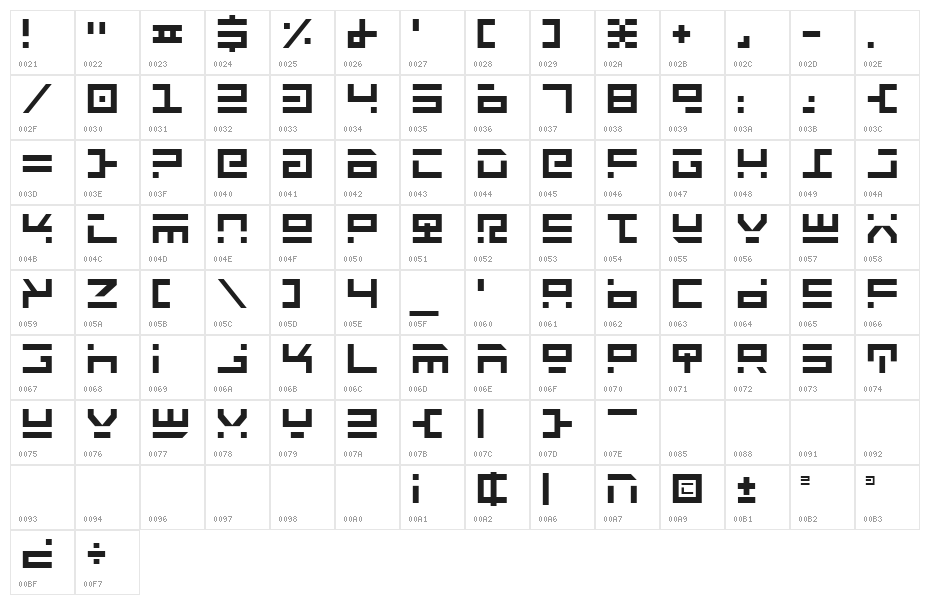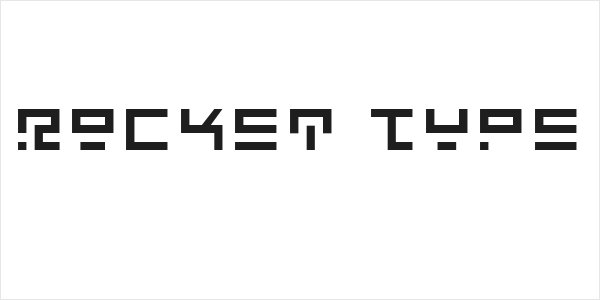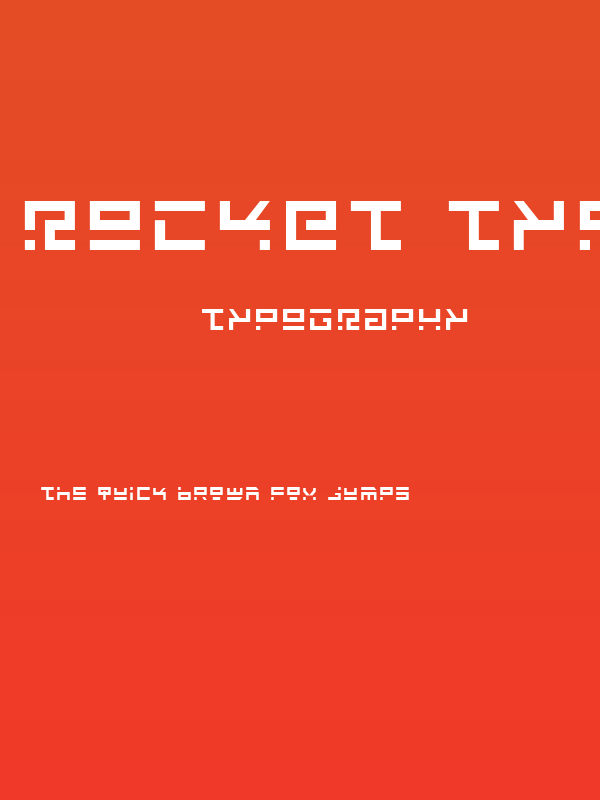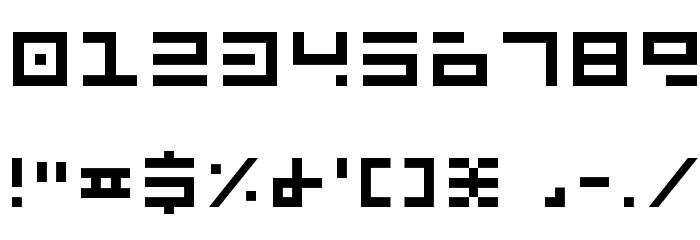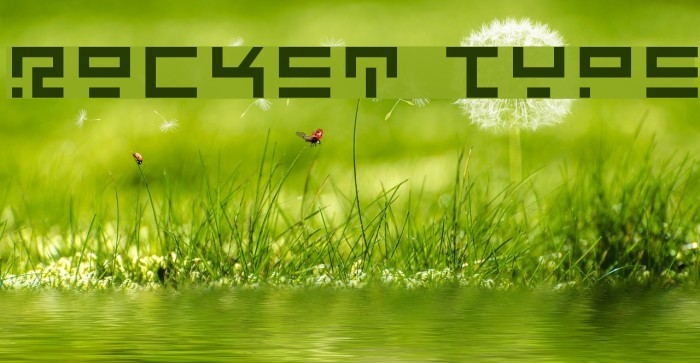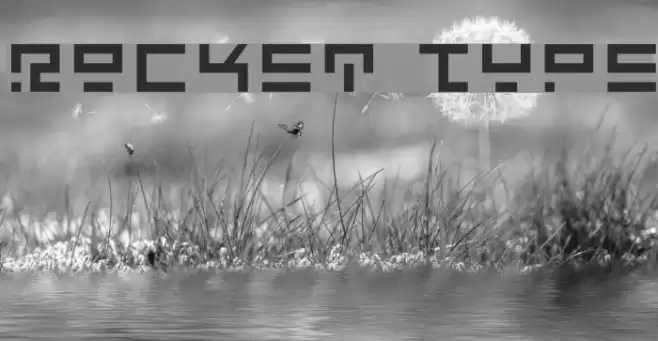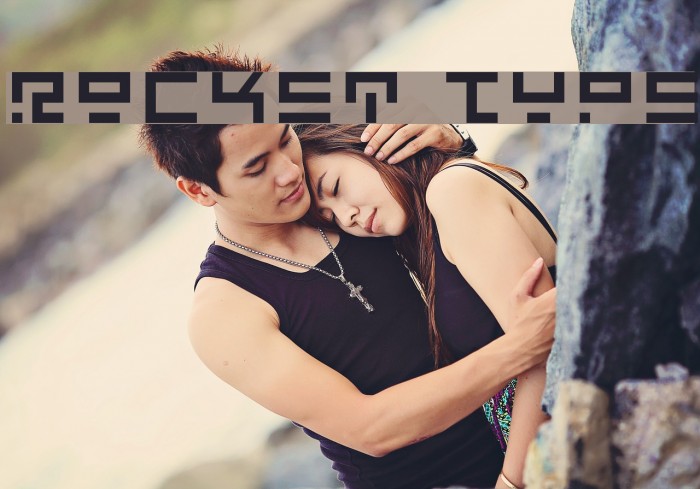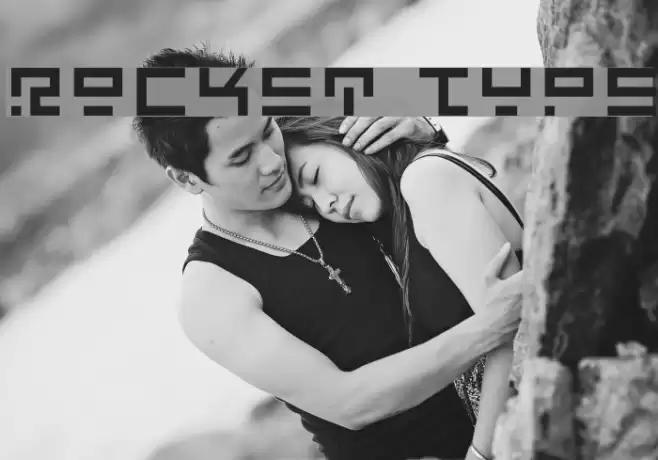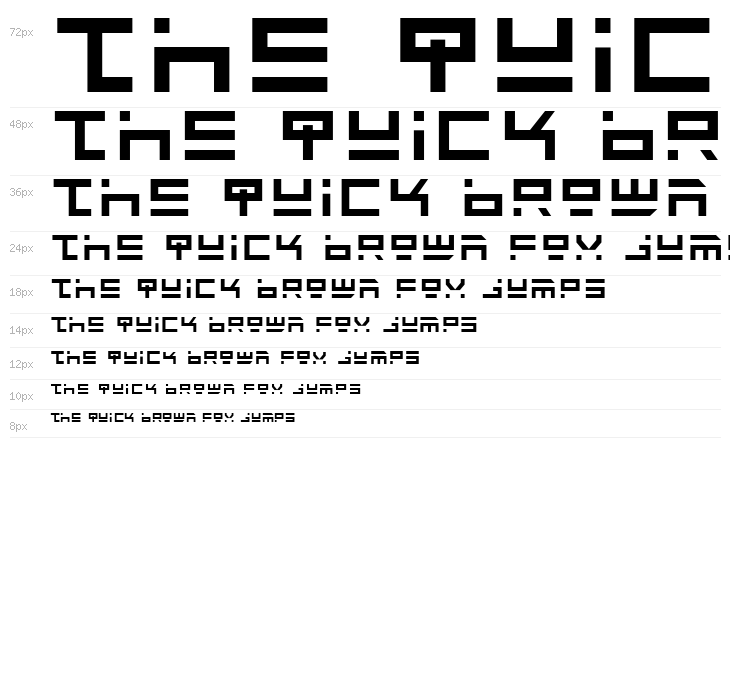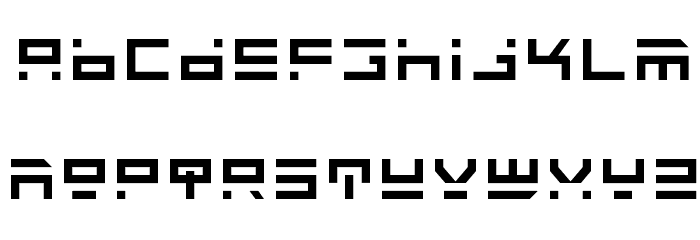
Rocket Type Font
✎ Futuristic
| Vorgeschlagene Projekte | Ideal for sci-fi movie posters, tech branding, video game interfaces, and futuristic-themed event invitations. |